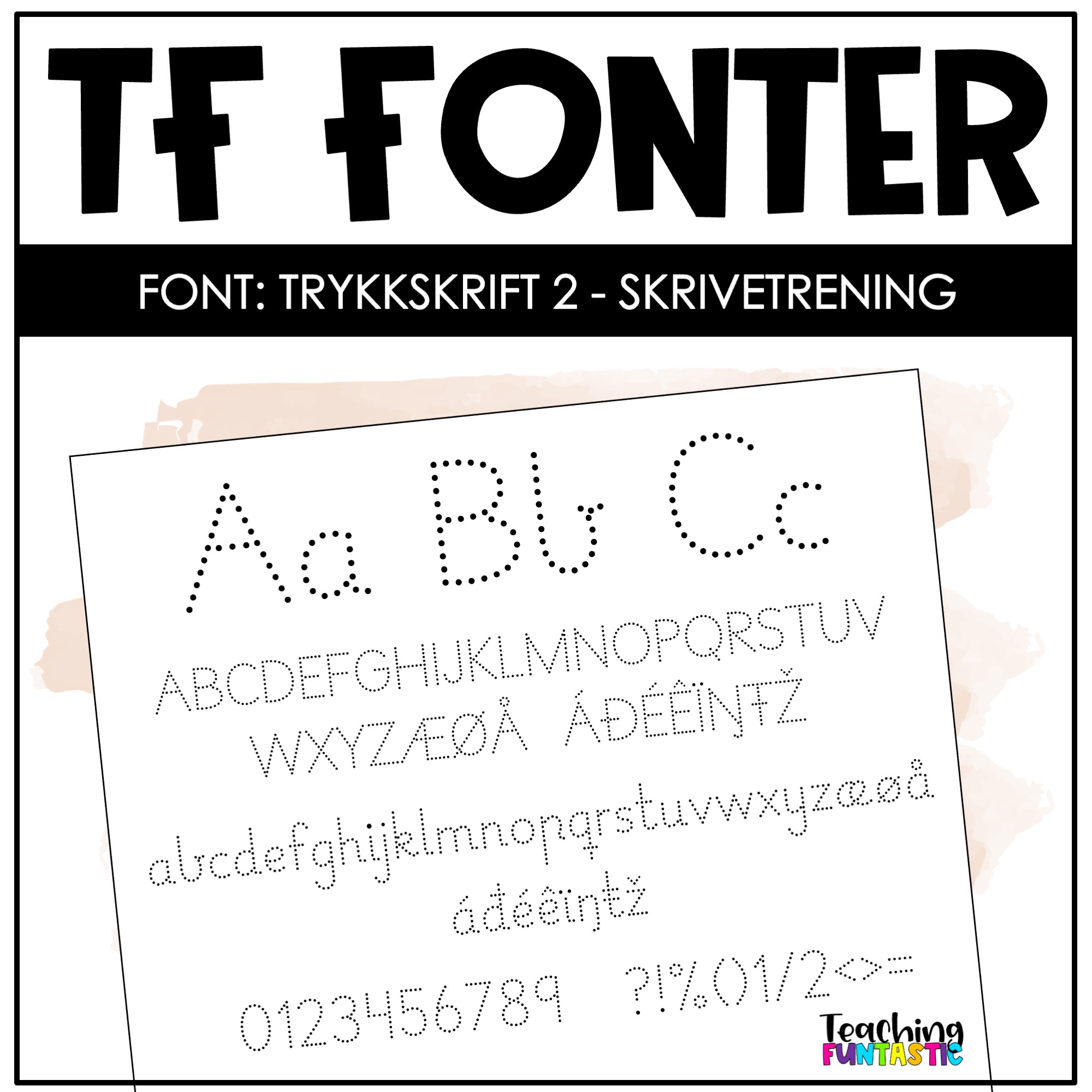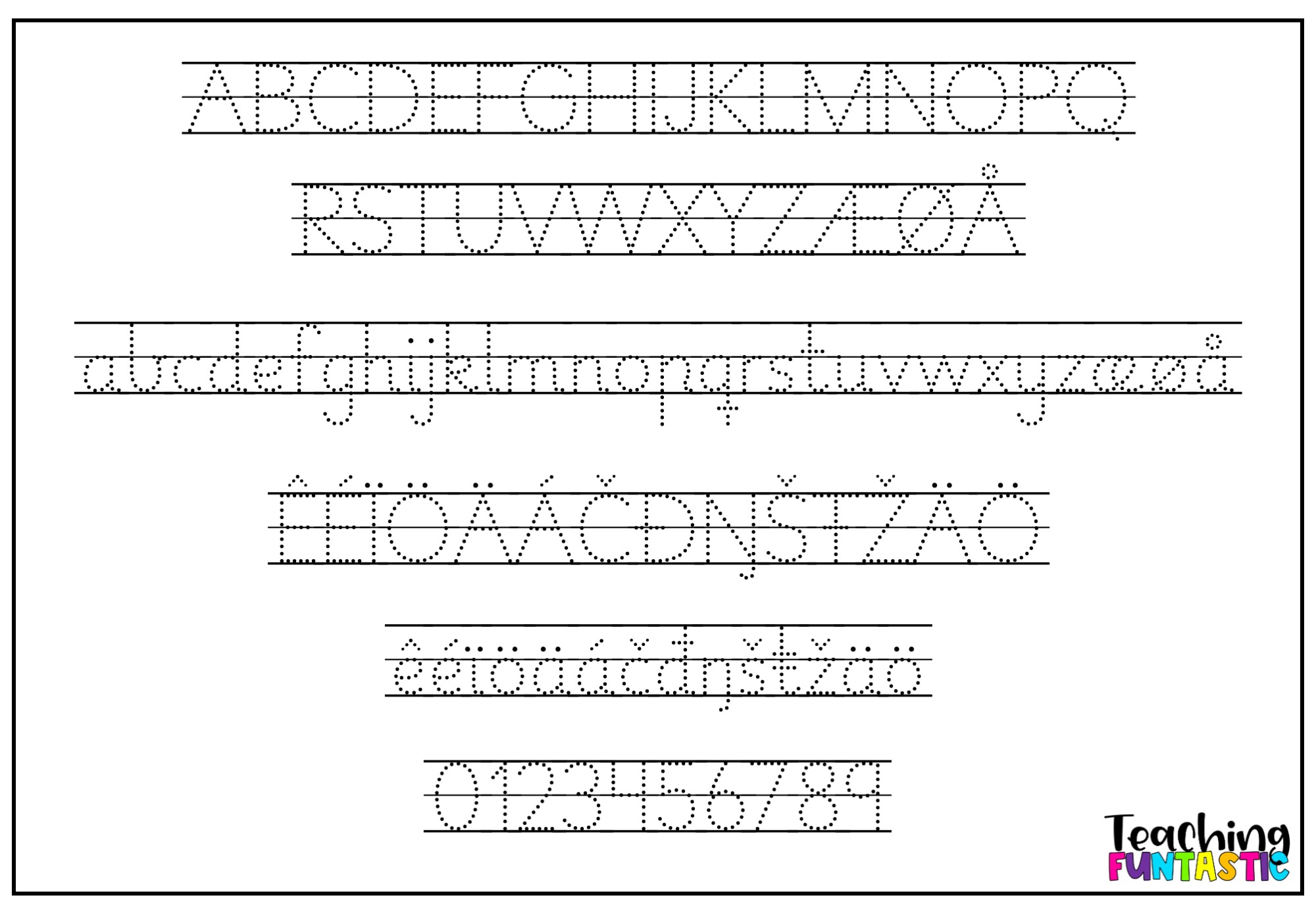
FUNtastic Trykkskrift 2 Skrivetrening – en font til trening av håndskrift
FUNtastic Trykkskrift 2 – Skrivetrening er en stiplet font som hjelper elever å øve på bokstavforming på en enkel og motiverende måte. Fonten er laget spesielt for lærere som ønsker å lage egne arbeidsark for skrivetrening i begynneropplæringen.
Denne fonten for skole og undervisning følger samme bokstavform som den vanlige FUNtastic Trykkskrift 2, men hver bokstav er bygget opp av små prikker. Det gjør det lett for elevene å følge linjene, trene håndbevegelsen og utvikle riktig blyantgrep og skriveflyt.
I denne fonten har bokstavene “hale”, og åpen b og p, slik at det blir enklere for elevene å binde sammen bokstavene senere.
Perfekt for skrivetrening i begynneropplæringen
Når barn lærer å skrive, er det viktig at de øver med tydelige, gjenkjennelige bokstavformer. Med denne stiplete fonten kan læreren raskt lage tilpassede oppgaver som bokstavark og skriveøvelser. Elevene får øve både motorisk og visuelt, med bokstavformene de ellers lærer å lese og skrive. Det gir trygghet og mestring i skriveprosessen – spesielt for elever som trenger mer støtte i finmotorikk og formgjenkjenning.
En font håndskrift laget for lærere
Norsk font med alle bokstaver
Fonten inkluderer alle de norske og samiske bokstavene. Bokstavene har balansert høyde og avstand for best mulig lesbarhet, både på skjerm og utskrift.